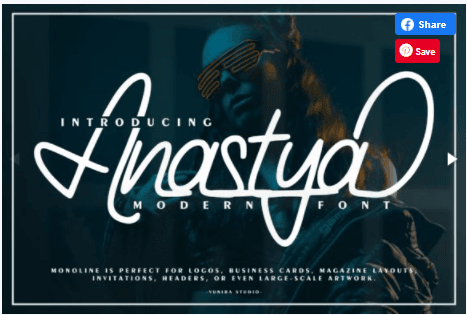
Anastya Font
Anastya - это хорошо сбалансированный и красивый рукописный шрифт с невероятно аутентичным ощущением. Этот уникальный шрифт без труда превратит любой дизайн-проект в особенный!